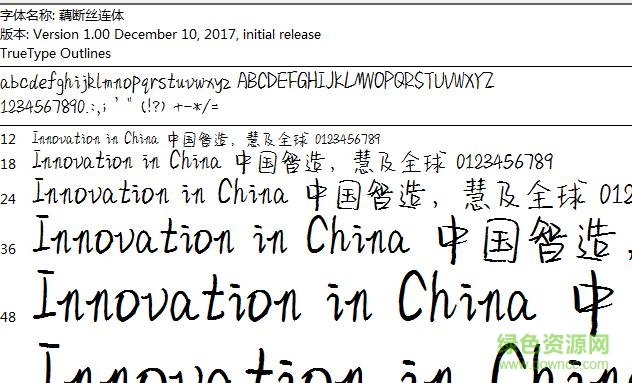
藕斷絲連字體ttf是一款小清新類(lèi)型的字體,這款字體被作者賦予了自然、隨性的特色,有喜歡這款字體的歡迎來(lái)綠色資源網(wǎng)免費(fèi)下載使用!
藕斷絲連字體ttf是一款硬筆手寫(xiě)字體,這款字體最大的特色的特色就是收筆的時(shí)候會(huì)有點(diǎn)連著,看上起非常的灑脫,長(zhǎng)時(shí)間的欣賞也不會(huì)覺(jué)得乏!.